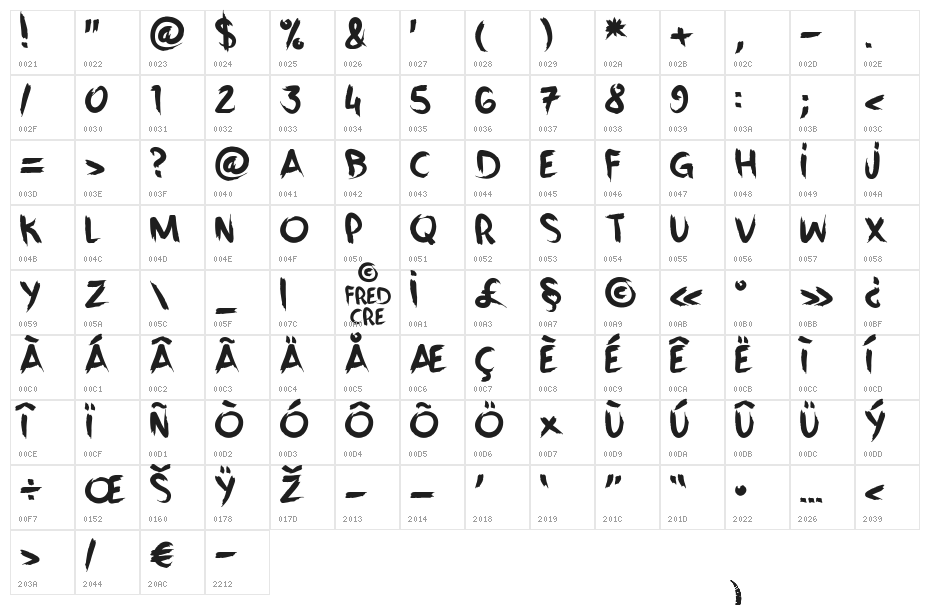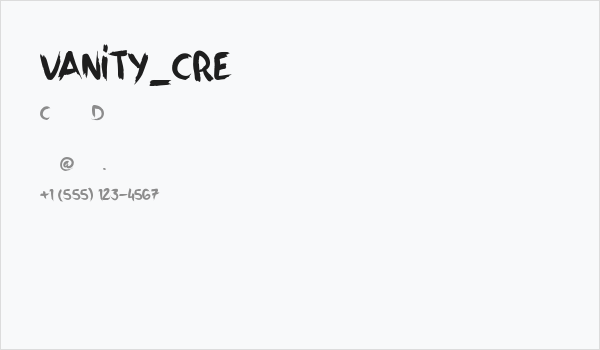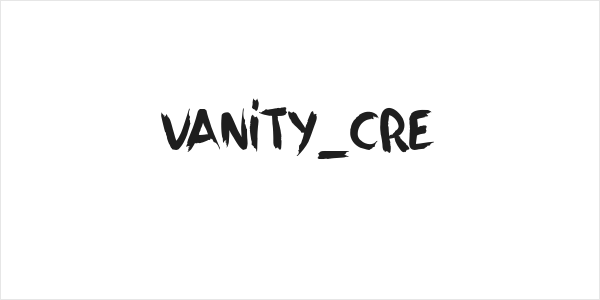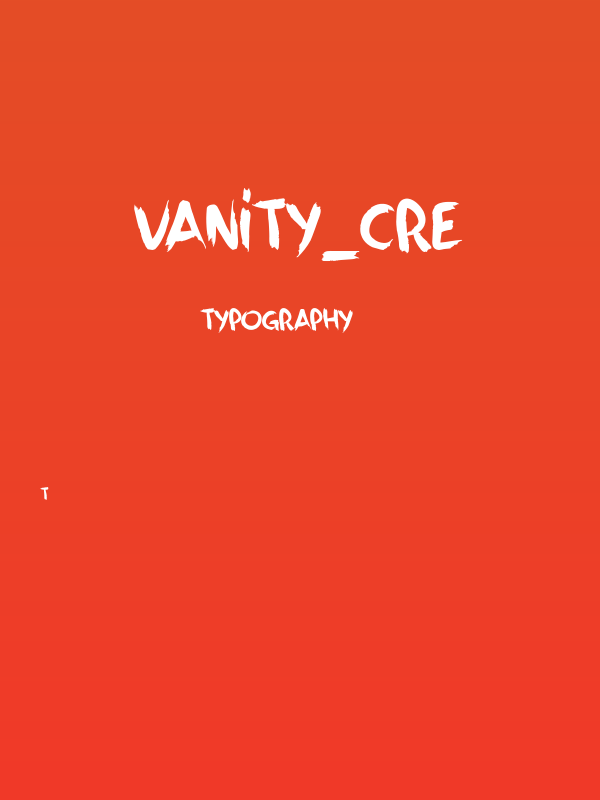
VANITY_CRE Font
✎ Thick
| النمط العام | Modern, Artistic |
| مشاريع مقترحة | Ideal for posters, album covers, branding, and any creative projects that require a bold and artistic touch. |